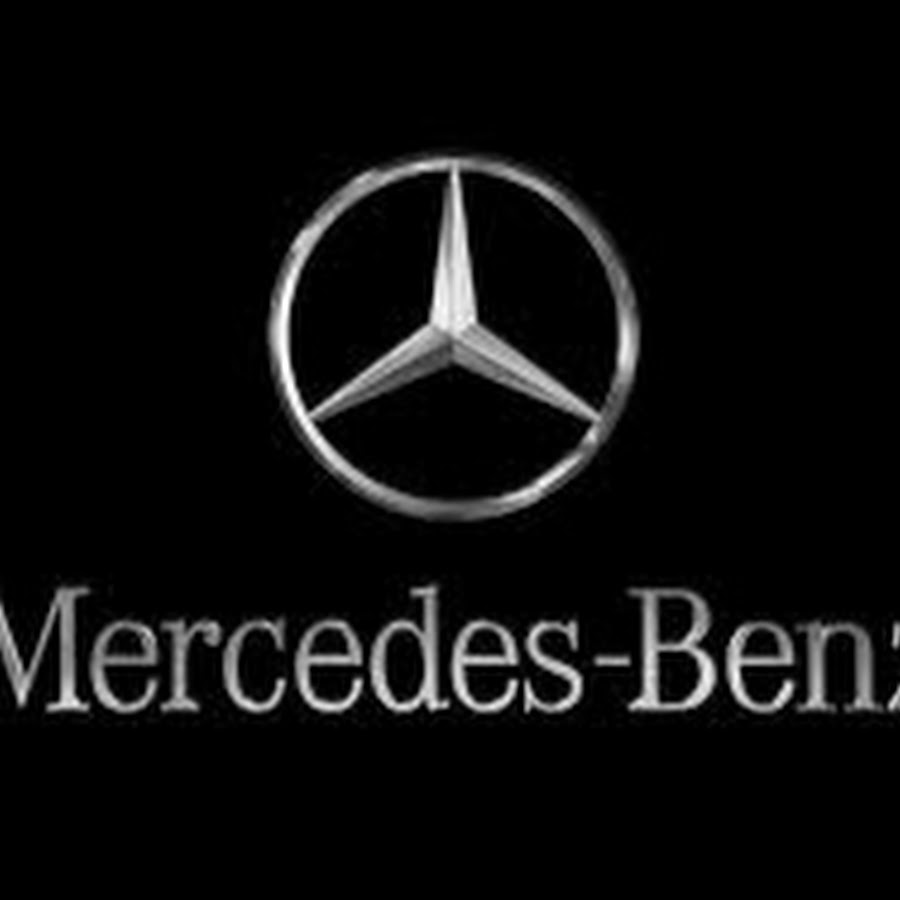
Интересные факты о дизайне: Фирменный шрифт: conjure — LiveJournal
Каждая уважающая себя компания или организация рано или поздно сталкивается с проблемой единого фирменного стиля.
От того, насколько быстро потенциальный клиент или потребитель распознаёт ту или иную марку, зависят порою не только объёмы продаж выпускаемых продуктов, но и положительные эмоции, способствующие более выгодному позиционированию марки на рынке и, как следствие, лучшим продажам.
К сожалению, многие заказчики упускают из вида, что частью фирменного стиля, способствующего формированию восприятия целого бренда, является шрифт: выбранная гарнитура, размер, соответствие продукту и многое другое.
Бренды должны «говорить» на своём индивидуальном языке. А шрифт, как сказал известный немецкий типограф Эрик Шпикерман (нем. Eric Spikermann, *1947), — это визуальный язык. {1}Если использовать банальный и избитый шрифт, сам бренд и его продукция или аудиовизуальные материалы станут банальными и даже незаметными.
Чтобы избежать банальности и незаметности, около 1985 года компания Mercedes обратилась за дизайном фирменного стиля, который включал в себя и разработку корпоративного шрифта, к известному дизайнеру и типографу Курту Вайдеману (нем. Kurt Weidemann, 1922-2011). Работа продлилась около 4х лет.
Если даже такой концерн как Mercedes на протяжении порядка 100 лет не боится перемен и неустанно работает над улучшением не только своей продукции, но маркетинговых стратегий, к которым относится и единый, последовательный фирменный стиль, чем ваша компания хуже?
Эрик Шпикерман в своей книге «О шрифте» {1} говорит, что раньше проектировать или переделывать шрифт было дорого и затруднительно.
Теперь же, в эпоху цифровых технологий, подобный шрифт можно заказать у любого дизайнера шрифтов — типографа.
По Шпикерману:
Дизайнеры шрифтов снабдят вас и одним начертанием для конкретного продукта, и большой системой для всех нужд.
Курт Вайдеман создал для компании Mercedes целую шрифтовую семью Corporate A-S-E. {2} Речь о следующих трёх гарнитурах шрифтов:
— Corporate A относится к шрифтовой семье Антиква — шрифт с засечками — и используется компанией для легковых автомобилей;
— Corporate E относится к семье Эгиптьен, он же брусковый шрифт, и используется для инженерных разработок.
На свет появились три фирменные гарнитуры шрифта, которые используются по сей день не только для продукции компании, но и для каталогов, рекламной продукции, для оформления автомобильных салонов, корреспонденции, а так же для визитных карточек служащих Mercedes по всему свету.
Индивидуальный шрифт, разработанный специально для вашей компании — это не роскошь, а необходимость. Не только возможность заявить о себе, но и организовать внутреннюю работу фирмы так, чтобы какой-нибудь новичок-дизайнер не оформил вашу продукцию самым ненавистным шрифтом Comic Sans 🙂